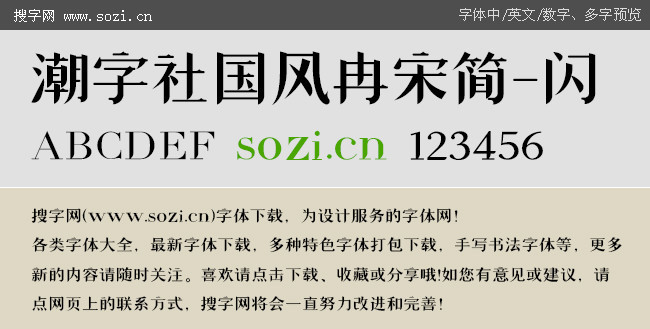
潮字社國風冉宋簡-閃
搜字網提供一款潮字社國風冉宋簡-閃中文字體下載,潮字社國風冉宋簡融合了古典與現(xiàn)代的視覺表現(xiàn),呈現(xiàn)出新國風的一種表達方式。這款字最大特點是銳而趨圓、彎則連勾、張馳有度,整體散發(fā)出一種韻律感,使字體結構自然、灑脫、儒雅還有一點點小可愛。,可用于出版和印刷,文學雜志,海報設計等應用。(本字體為個人非商用版,商用請聯(lián)系作者購買授權)